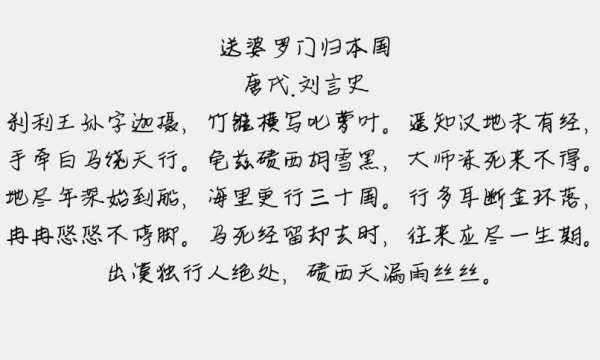
爱的飞行日记字体是根据周杰伦同名歌而制作的一款手写的钢笔行书字体,该字体笔画起收有序、笔笔分明、坚实有力、停而不断、直而不僵、流畅自然,同时字体的角度、大小、距离都设计得非常恰当,整体效果极佳,可很好的应用于文本装潢、信息展示、网页设计、篆刻制模、数据制作、装潢设计、计算艺术设计、视觉设计、字帖等一切合法应用场景,有喜欢的朋友可免费下载收藏。